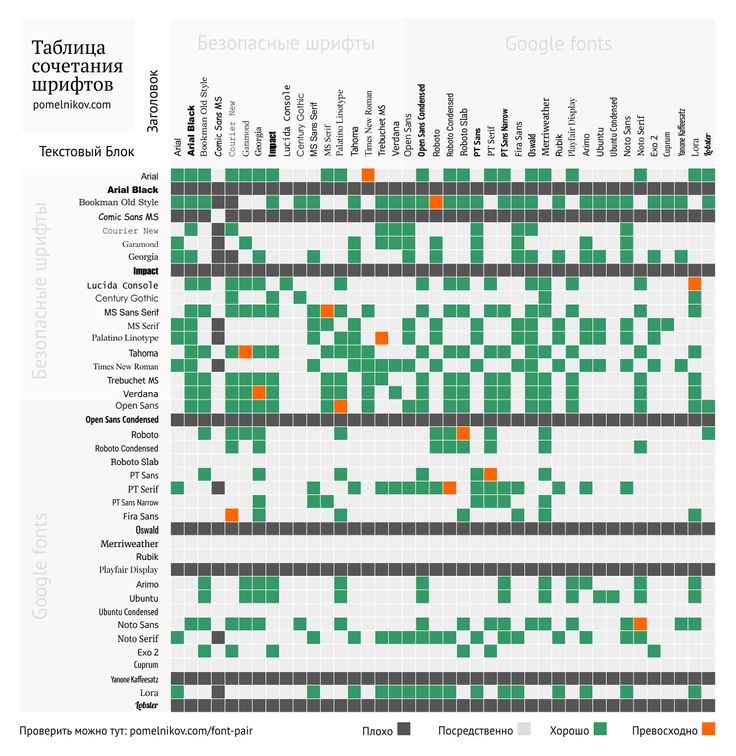
Убедитесь, что вы используете веб-безопасные шрифты
Текст является одним из наиболее важных аспектов внешнего вида сайта. Чтобы посетители сайта увидели ваш сайт в стиле, который вы тщательно продумали, выберите веб-безопасные шрифты.
Краткая история шрифтов в Интернете
В течение многих лет веб-дизайнерам приходилось использовать несколько шрифтов, которые были найдены на большинстве компьютеров. Они были известны как веб-безопасные шрифты. Возможно, вы слышали этот термин в прошлом от веб-дизайнера, который пытался объяснить, почему определенный шрифт не может быть использован в дизайне вашего сайта .
Тем не менее, за последние несколько лет веб-типография прошла долгий путь, и веб-дизайнеры и разработчики больше не ограничены лишь несколькими веб-безопасными шрифтами. Распространение веб-шрифтов и возможность ссылаться на файлы шрифтов открыли новый мир возможностей для использования шрифтов сайта. Однако столь же полезный, как и доступ к этим вариантам шрифтов, эти проверенные веб-безопасные шрифты по-прежнему занимают важное место в современном веб-дизайне.
Ссылки на веб-шрифты
Чтобы использовать шрифты, которые обычно не установлены на большинстве компьютеров, попросите ваш веб-сайт использовать внешний файл шрифтов онлайн или включите шрифт в ресурсы вашего сайта вместо того, чтобы смотреть на компьютер посетителя сайта. Это дает вам практически неограниченный выбор шрифтов, но это преимущество имеет свою цену. Внешние шрифты должны загружаться на сайт, что влияет на скорость загрузки сайта.
Таким образом, веб-безопасные шрифты являются хорошим выбором, если время загрузки страницы учитывается. Поскольку эти файлы шрифтов находятся на компьютере посетителя, при загрузке веб-сайта производительность не снижается. Вот почему многие веб-дизайнеры используют сочетание внешних веб-шрифтов и надежных веб-безопасных шрифтов в стеках шрифтов своих сайтов . Этот подход предлагает дизайн стильных шрифтов с ориентацией на производительность сайта.
Sans-Serif Web-Safe Шрифты
Эта семья — один из лучших вариантов для веб-безопасных шрифтов.
Почти все посетители сайта увидят это так, как вы хотели. Вот некоторые распространенные веб-безопасные шрифты без засечек :
- Arial
- Arial Black
- Tahoma
- Требушет М.С.
- Verdana
Это простые, четкие, легко читаемые шрифты без орнамента.
Другие варианты без засечек обеспечивают хорошее общее покрытие, но могут отсутствовать на некоторых компьютерах. Просто не забудьте включить один из списка выше в стек шрифтов в качестве резервной копии.
- В. Готика
- Женева
- Lucida
- Люцида Санс
- Люсида Гранде
Serif Web-Safe Шрифты
Семейство шрифтов с засечками — еще один популярный выбор для веб-сайтов. Вот некоторые из ваших самых безопасных ставок в шрифтах с засечками:
- курьер
- Новый Курьер
- Грузия
- раз
- Times New Roman
Ниже приведены некоторые шрифты, которые установлены на многих компьютерах, но имеют меньший общий охват, чем приведенный выше список.
Вы можете использовать эти шрифты надежно, но в свой стек шрифтов следует включить более распространенный шрифт с засечками (из списка выше).
- MS Serif
- Нью-Йорк
- Palatino
- Палатино Линотип
Моноширинные шрифты
Хотя не так широко используются шрифты с засечками и без засечек, моноширинные шрифты также являются опцией. Они имеют одинаково распределенные буквы и не имеют широкого распространения на разных платформах:
- курьер
- Новый Курьер
Эти шрифты также имеют некоторое покрытие:
- Lucida Console
- Монако
Курсивные и Фантазийные Шрифты
Курсивные и фэнтезийные шрифты не так популярны, как шрифты с засечками или без засечек, а витая природа этих шрифтов делает их неподходящими для основного текста. Эти шрифты часто появляются в заголовках и задаются шрифтами большого размера для коротких пакетов текста. Стилистически эти шрифты могут выглядеть великолепно, но удобочитаемость перевешивает стиль в Интернете.
На компьютерах Windows и Apple доступен только один курсивный шрифт (но не в Linux): Comic Sans MS. Тем не менее, в последнее время он встречается с насмешками среди дизайнеров (в основном из-за его чрезмерного использования), поэтому избегайте его.
Смартфоны и мобильные устройства
Если вы создаете страницы для мобильных устройств , выбор шрифтов, безопасных для Интернета, может быть различным. Для устройств iPhone, iPod и iPad общие шрифты включают в себя:
- Arial
- курьер
- Новый Курьер
- Грузия
- Helvetica
- Palatino
- Times New Roman
- Требушет М.С.
- Verdana
Веб-шрифты являются отличным выбором для дизайна нескольких устройств. Возможность загрузки внешних шрифтов обеспечивает более согласованный вид от устройства к устройству. Затем вы можете настроить эти загруженные шрифты на один или два безопасных для сети варианта, чтобы получить внешний вид и производительность, необходимые для успеха вашего сайта.
Из-за отсутствия поддержки мы создали стеки шрифтов в редакторе (используя каскадные таблицы стилей), которые автоматически сообщают любой программе электронной почты, как «откатиться» к безопасному шрифту, когда этот почтовый клиент не может их отобразить. . Стеки работают как список потомков вариантов: если первый недоступен, он переходит к следующему.
Наборы шрифтов
Шрифты сгруппированы вместе, чтобы предложить наилучшее резервное решение. Это гарантирует, что макет не сломается, если выбранный шрифт не поддерживается.